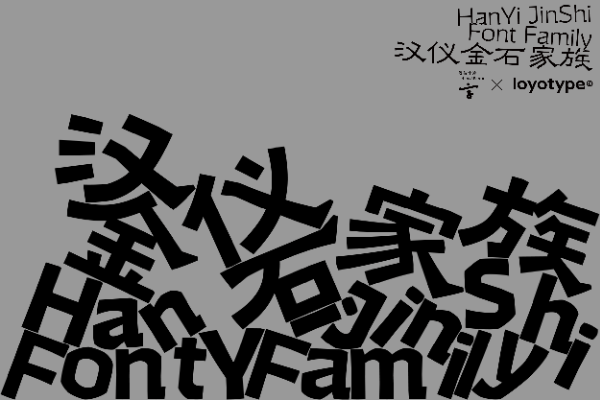
汉仪金石 95W
汉仪金石家族的设计灵感汲取自两汉隶书的深厚底蕴,旨在传达生动自然、率真朴质、天真烂漫的美学理念。排印表现方面,汉仪金石家族 展现出统一而富有节奏的肌理,使得整体排版既匀称又富有变化。在多种应用场景中表现丰富的视觉层次与细腻的变化。无论是追求现代简约还是人文复古的画面呈现,汉仪金石家族字体都能提供恰当的视觉支撑,满足多样化的设计需求。